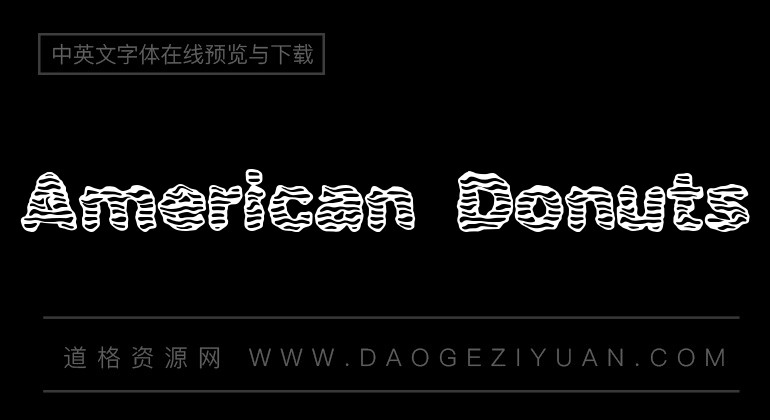
American Donuts 是一款由Fontfabric 公司设计的字体,它是一款美式风格的字体,具有粗犷、活泼、有趣的特点。它的字形充满了美式活力,适合用于各种商业广告、海报、网页设计等。它的字体也具有独特的外观,可以让文本更加有趣。内容介绍
American Donuts是一款非常不错的手写艺术字体,具有很好的视觉感,适合于文化类的宣传设计、商业类品牌的广告和产品包装设计以及个性化文字排版等较多场景。